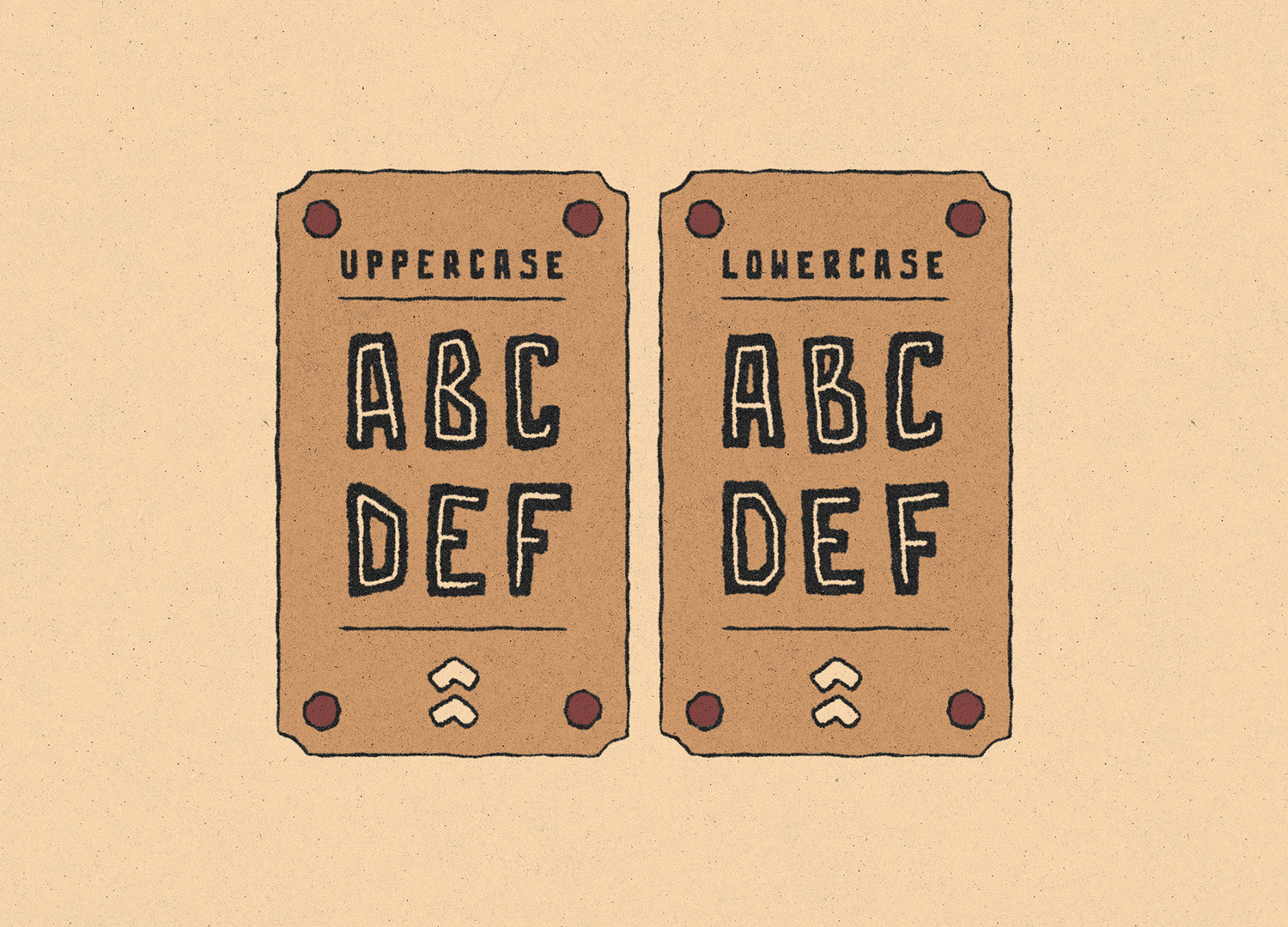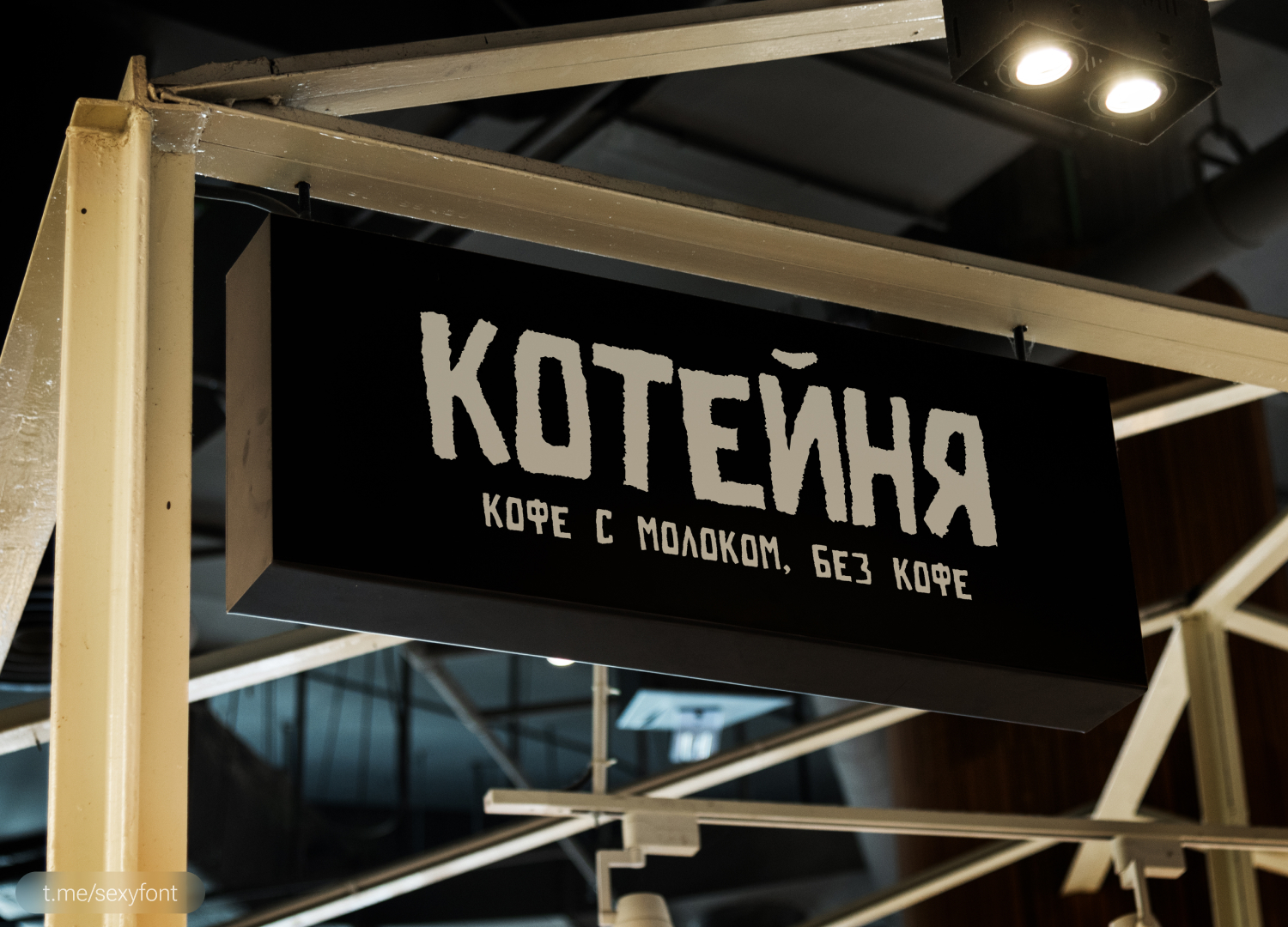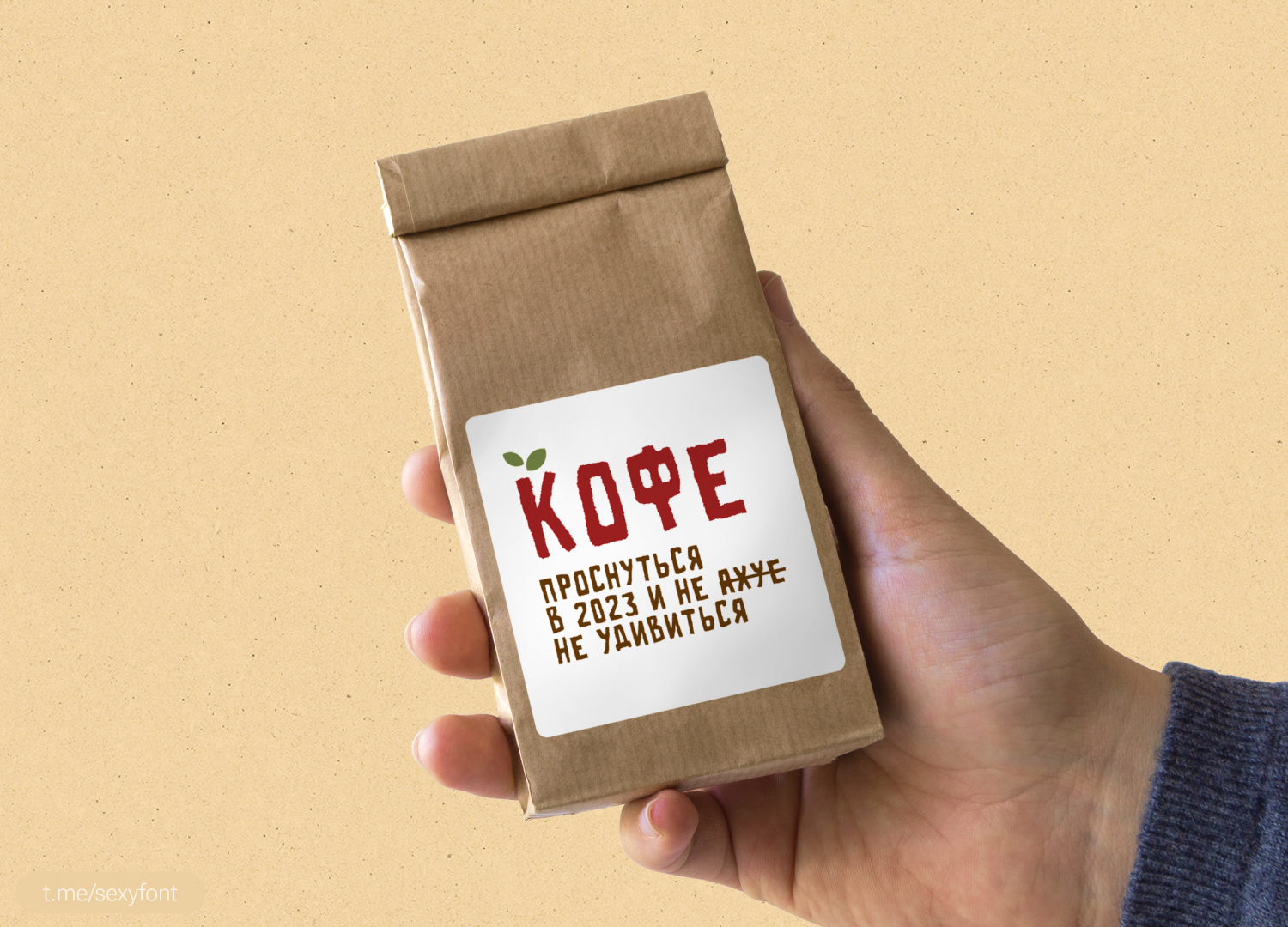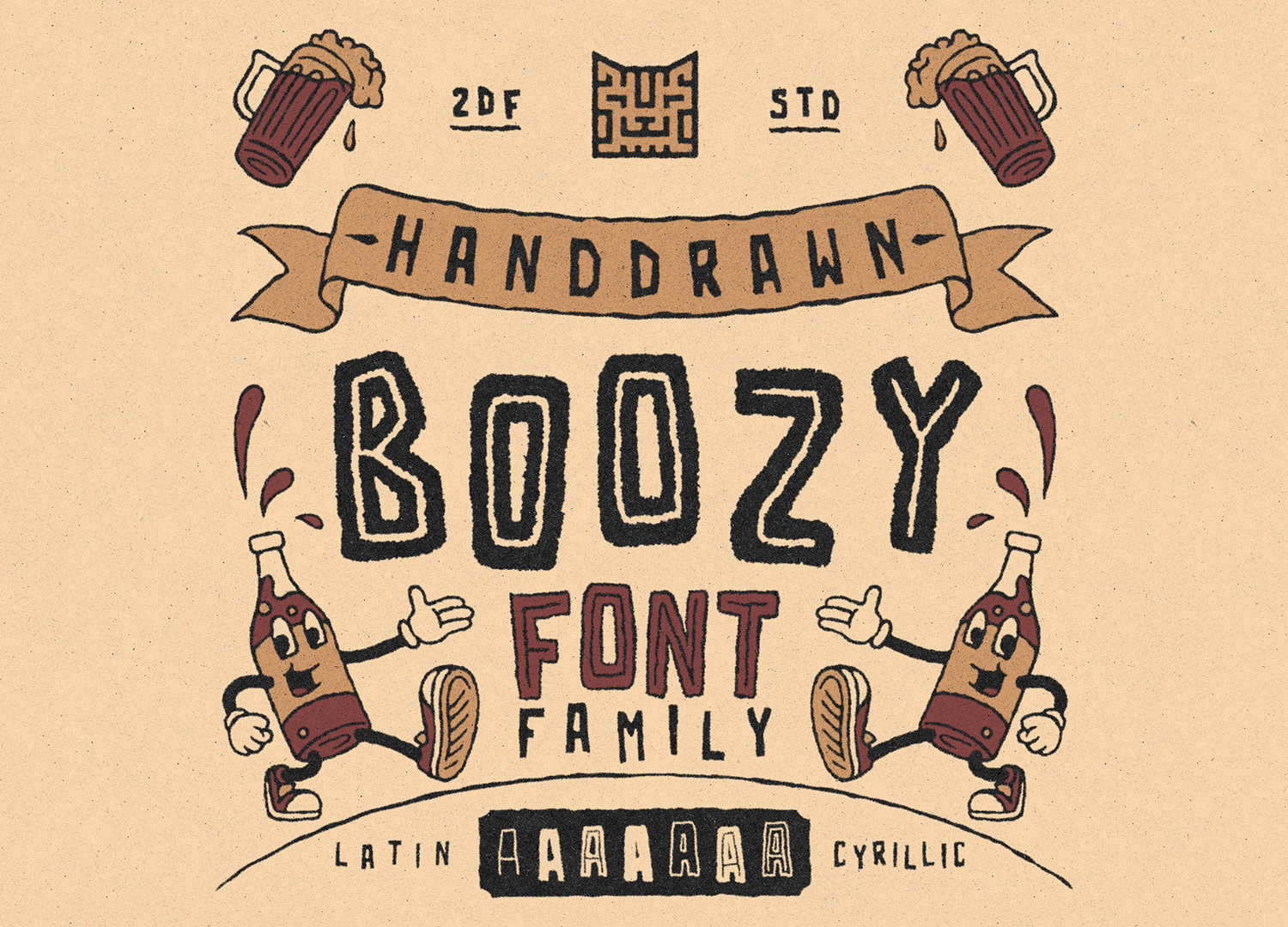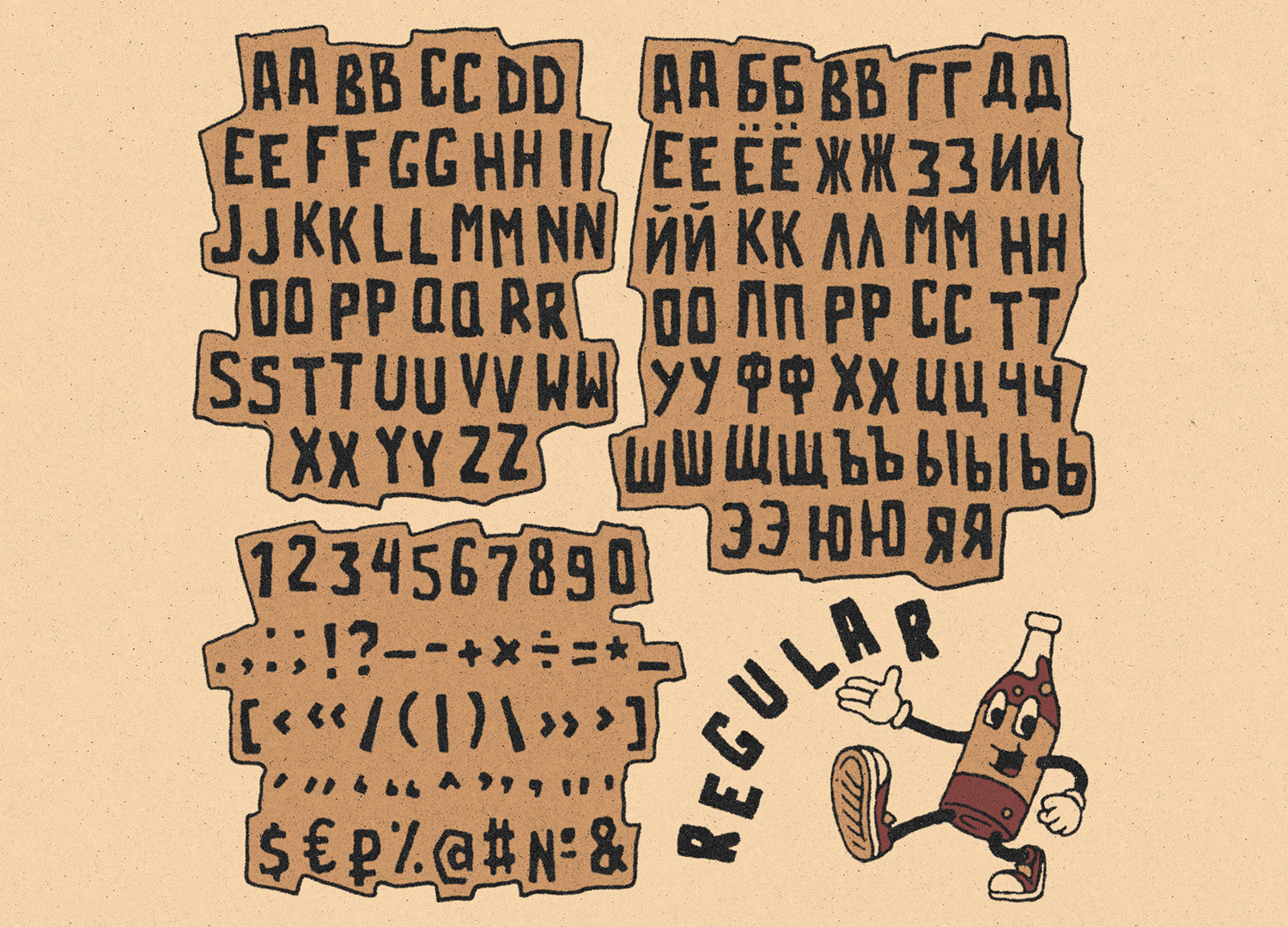
Boozy. Бесплатный кириллический шрифт
Не бузи кому говорю!) Держи вот новый, крафтовый шрифтец. «Бузи» называется.
Идеально для всяких упаковок, кофеен, надписей веселых.
Не бузи кому говорю!) Держи вот новый, крафтовый шрифтец. «Бузи» называется.
Идеально для всяких упаковок, кофеен, надписей веселых.